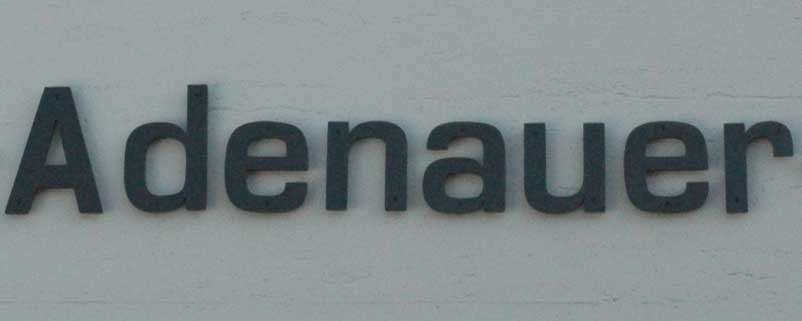
da ich dringend hilfe benötige wende ich mich an das typoforum und smoit an euch.
ich suche diesen font
ich dachte schon es seid die dinpro aber da scheine ich mich wohl geirrt zu haben.
also wenn da jemand rat weiss wäre das super!
Ja, das A ist verkehrt herum! Außerdem etwas schmaler als im Schrift-Sample